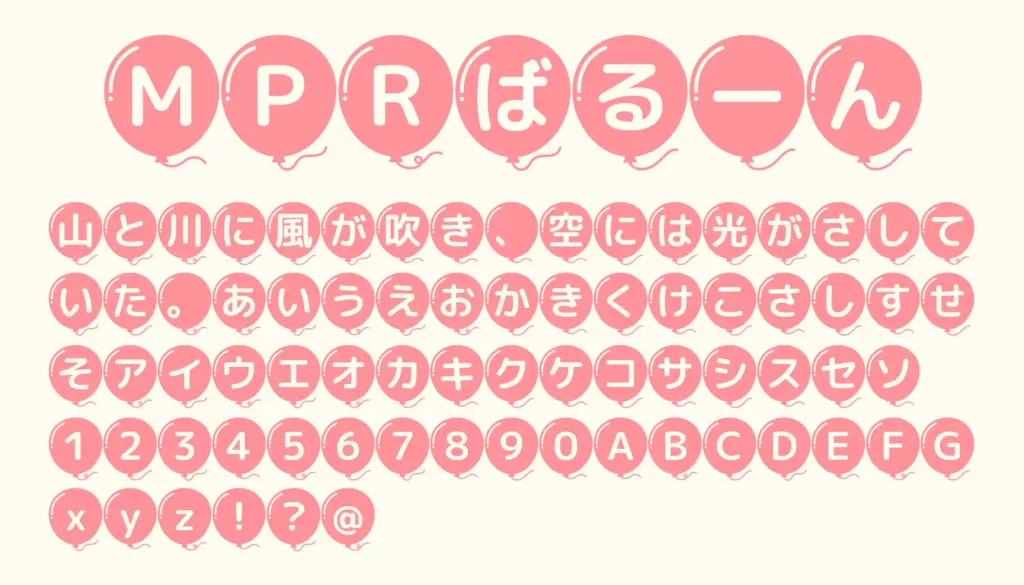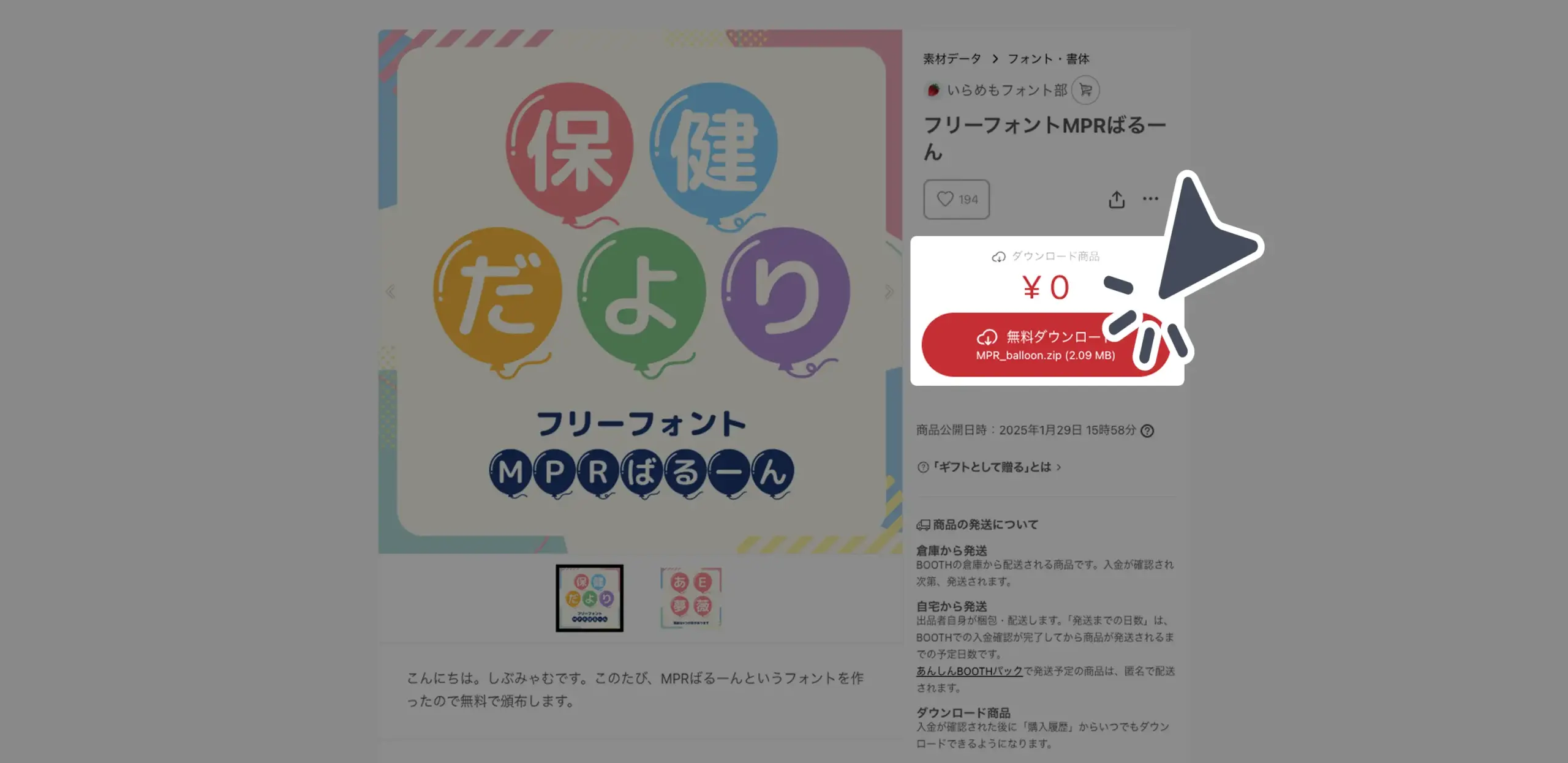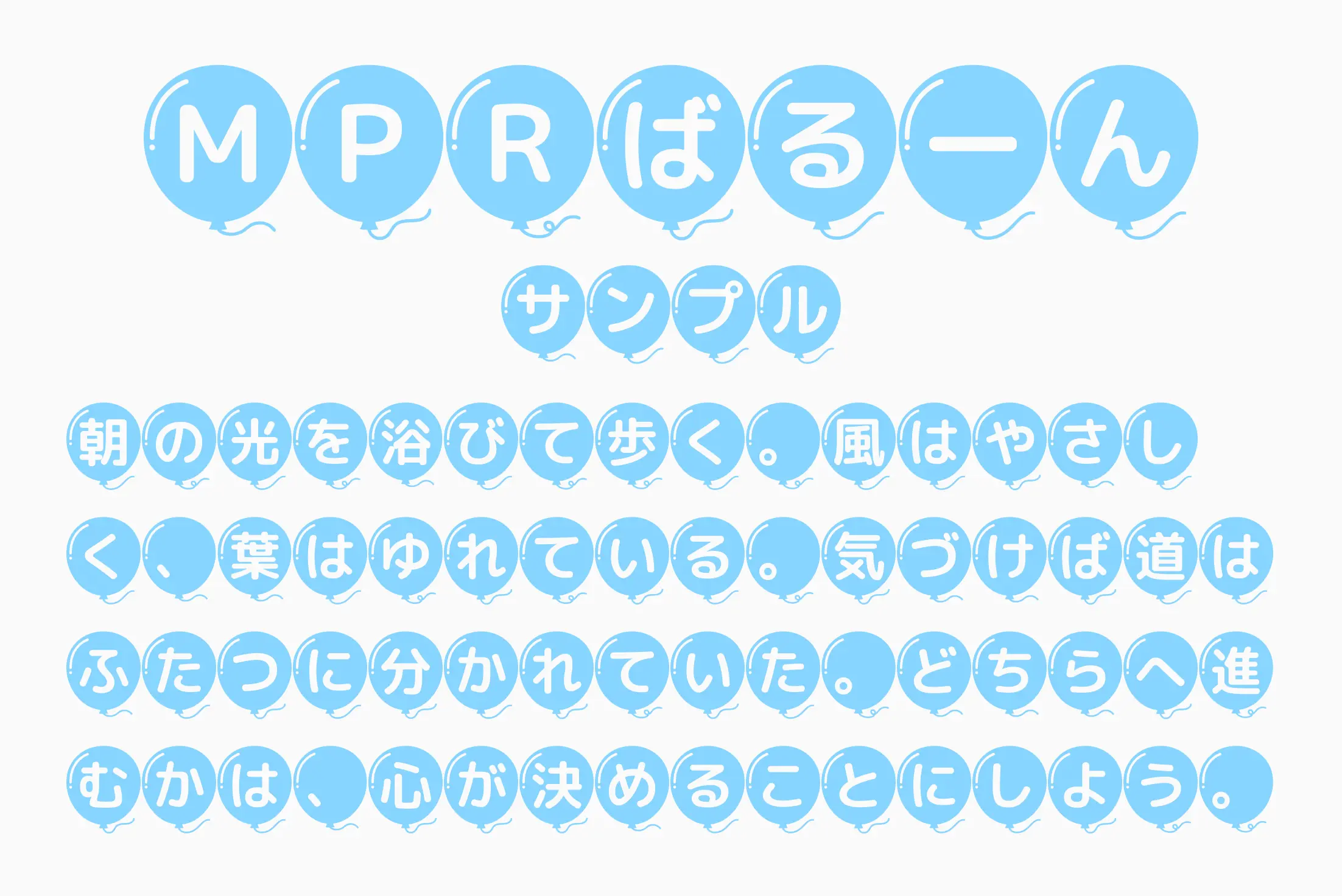
風船のようにぷっくりと膨らんだフォルムが印象的なフリーフォント。ひらがな・カタカナ・漢字まで対応しており、すべての文字にやさしい丸みとポップな楽しさが詰まっています。保育園や幼稚園のおたより、キッズイベントのポスター、YouTubeサムネイルなど「かわいく目立たせたい」シーンにぴったりの書体です。
MPRばるーん